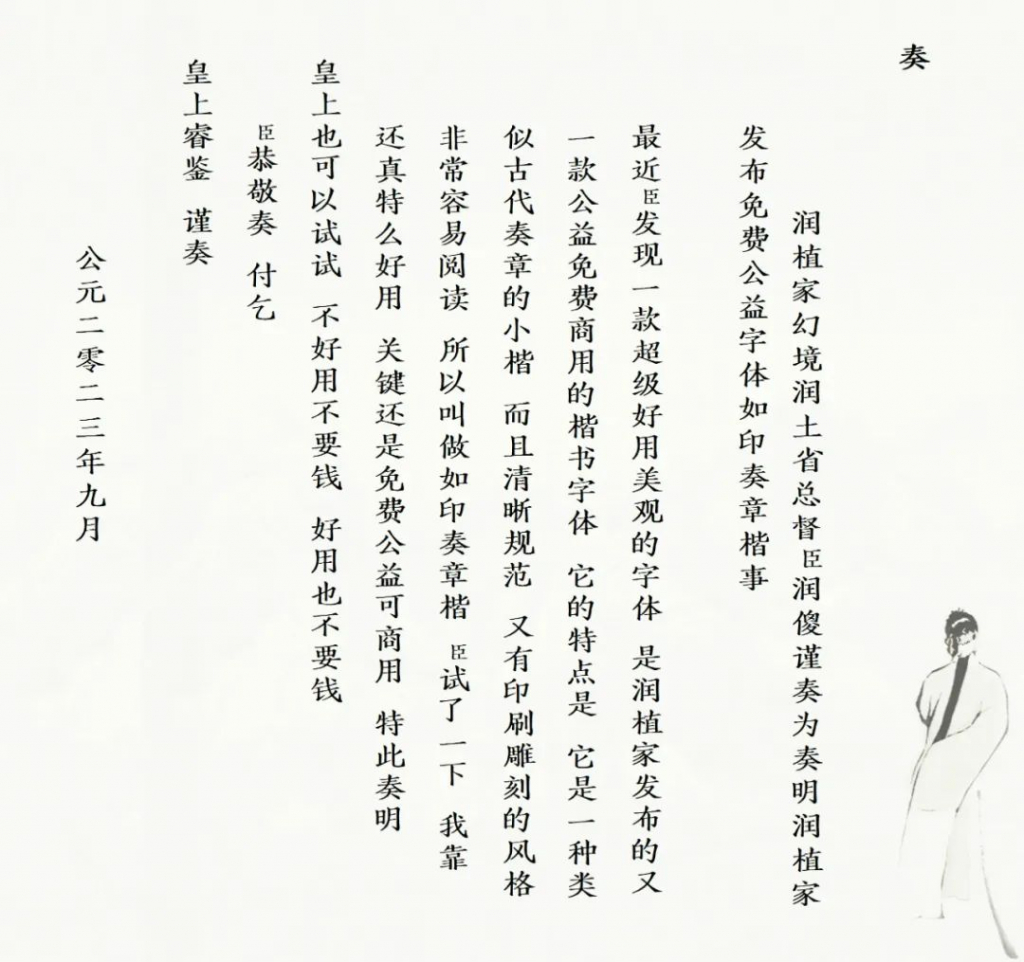
这款字体专用于大量文字,作为正文,竖排和横屏都好看,并且具有官方正式场合使用的气场,没有太大的违和感。
为什么叫如印奏章楷呢?因为这种规范中庸、有书卷气、可识别性高、适合长文阅读的字体,类似传统小楷书写的奏章,如果古代用这种字体写奏章,皇帝看了也会很舒服。
下面是模拟奏章的效果,是不是又平和工整、又养眼适合阅读?
同时,不光是直排的古代文字,横排也很好看,适合用于一些官方文件的展示哦,下面是用于官方文件展示的效果示例: